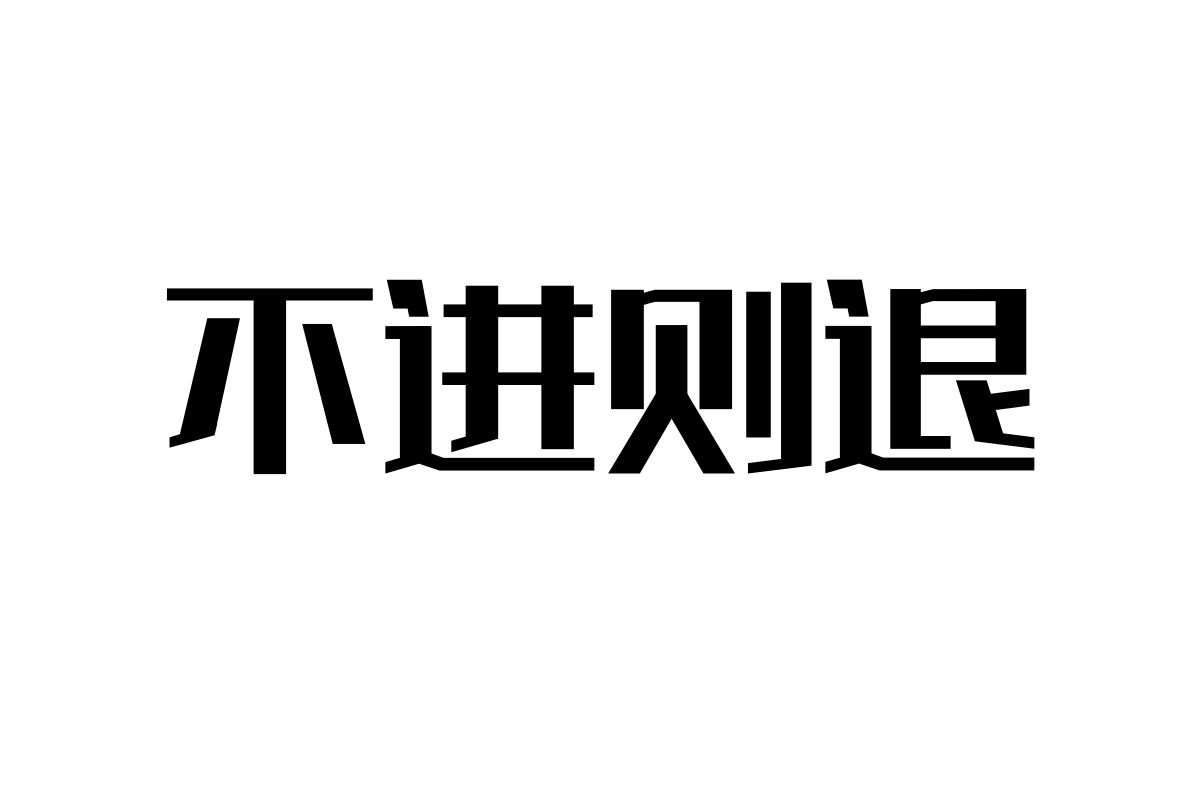
上首机甲体是一种具有科幻风格的字体,它模仿了未来科技和战争机器的形象。这种字体的特点是线条粗犷、有力,给人一种强烈的视觉冲击力。
上首机甲体的笔画粗细不一,有的尖锐如刀片,有的宽大如盾牌,有的弯曲如机械臂。这种独特的线条组合使得整个字体看起来既有力量感,又不失美感。
上首机甲体的字形结构紧凑而有力,每个字符都充满了动感。这使得整个字体在阅读时给人一种速度感和紧张感,仿佛置身于一个充满战斗和冒险的世界。
总的来说,上首机甲体是一种极具个性和特色的字体,它以其独特的线条和结构,展现了未来科技和战争机器的神秘魅力。